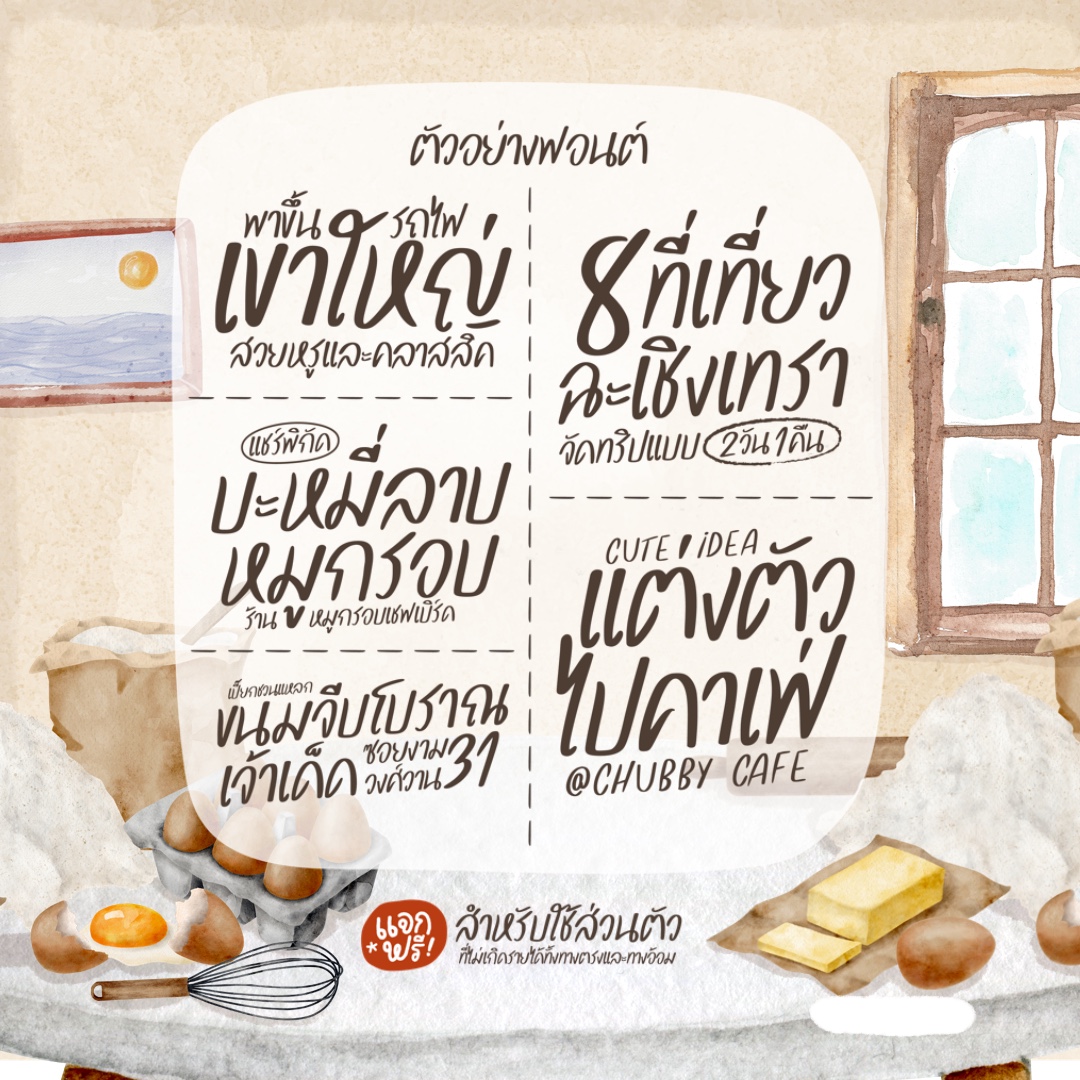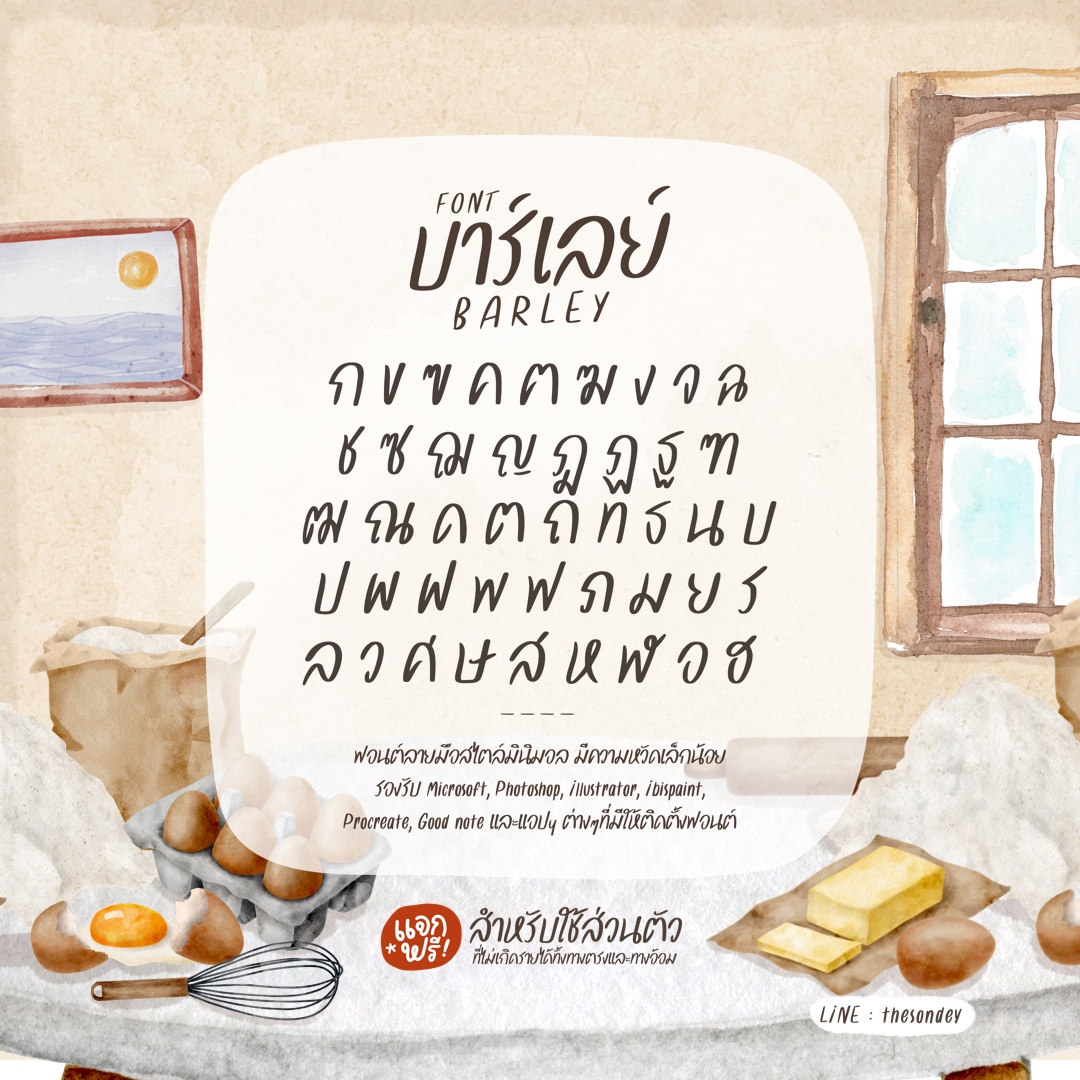
บาร์เลย์ (PG Barley)
ฟอนต์ลายมือสไตล์น่ารักปุ๊กปิ๊ก อ่านง่าย รองรับ Microsoft, Photoshop, Illustrator, CapCut, ibisPaint, Procreate, Good Note และแอปฯ ต่างๆ ที่มีให้ติดตั้งฟอนต์